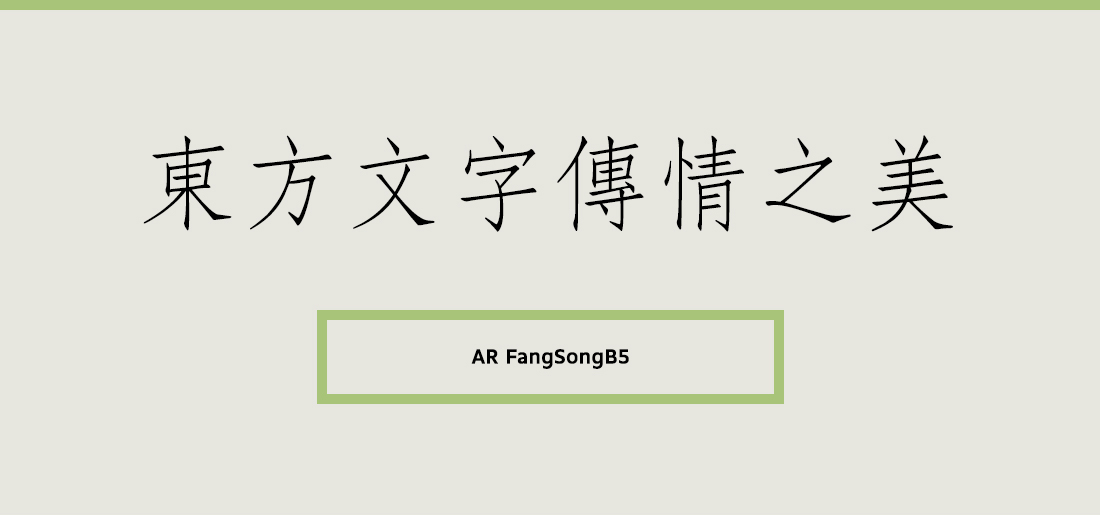
AR FangSongB5
FangsongB5는 전반적으로 곧고 균형잡힌 획을 갖고 있는 폰트이다.획의 너비가 일정하게 표현되어 있어 더욱 슬림하고 고전적인 느낌을 받으며 특히 수직 텍스트용으로, 제목이나 본문으로 기사에 유연하게 사용할 수 있다.폰트명 뒤에 붙은 B5라는 표기는 번체의 문자코드인 BIG5를 뜻한다. 번체란 중국을 제외한 대만, 홍콩, 마카오 등의 중화권 국가에서 사용하는 전통적인 모양의 한자다. 중국에서 사용하는 간체(GB)와는 달라 잘못 적용할 경우 글립이 제대로 표기되지 않거나 다른 글립으로 표기되는 문제가 발생할 수 있다.